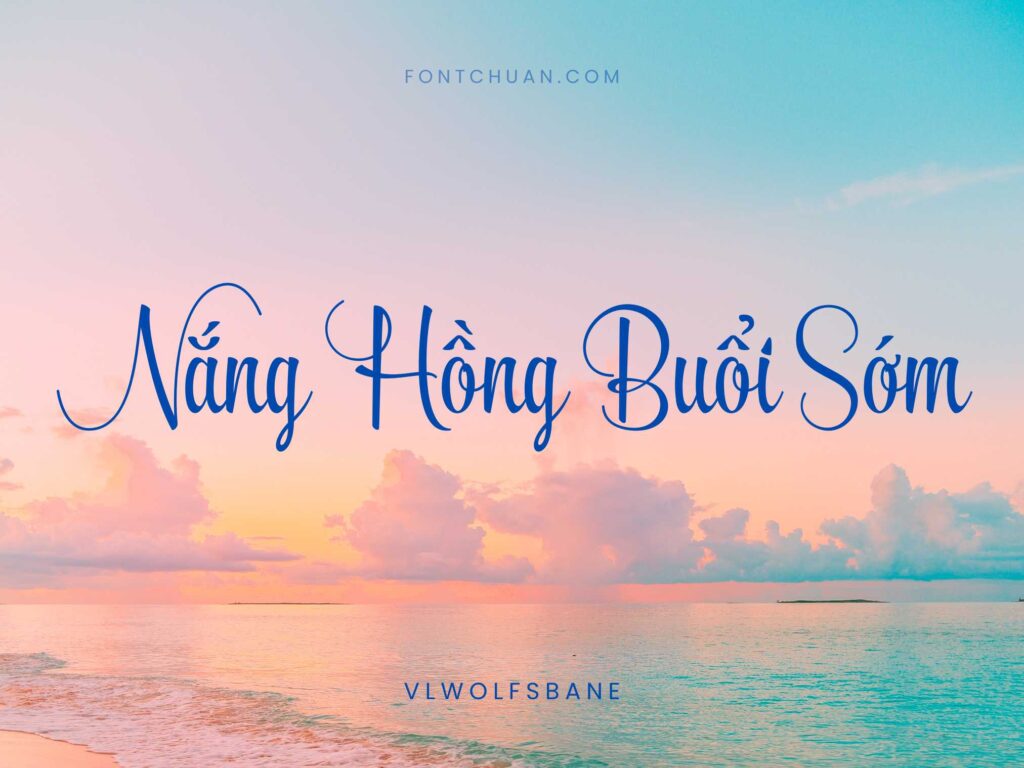
VL-WOLFSBANE là một phông chữ mạnh mẽ và đầy cá tính, mang phong cách đậm nét với thiết kế độc đáo. Được thiết kế bởi Iconian Fonts, phông chữ này phù hợp cho các dự án thiết kế như tiêu đề, áp phích, logo và các ấn phẩm quảng cáo. VL-WOLFSBANE đã được Việt hóa bởi Việt Linh, hỗ trợ đầy đủ các ký tự tiếng Việt, giúp người dùng dễ dàng áp dụng trong các dự án sáng tạo. Phông chữ này được thành viên Font Chuẩn sưu tầm và đăng tải nhằm phục vụ nhu cầu thiết kế đa dạng.
Với thiết kế mạnh mẽ và phong cách riêng biệt, VL-WOLFSBANE phù hợp cho các ứng dụng như tiêu đề, áp phích, logo và các ấn phẩm quảng cáo. Trong lĩnh vực sự kiện, phông chữ này có thể được sử dụng trong các dịp như lễ hội, Halloween và các sự kiện sáng tạo. Ngoài ra, VL-WOLFSBANE cũng thích hợp cho các ngành nghề như quảng cáo, giáo dục và công nghệ.